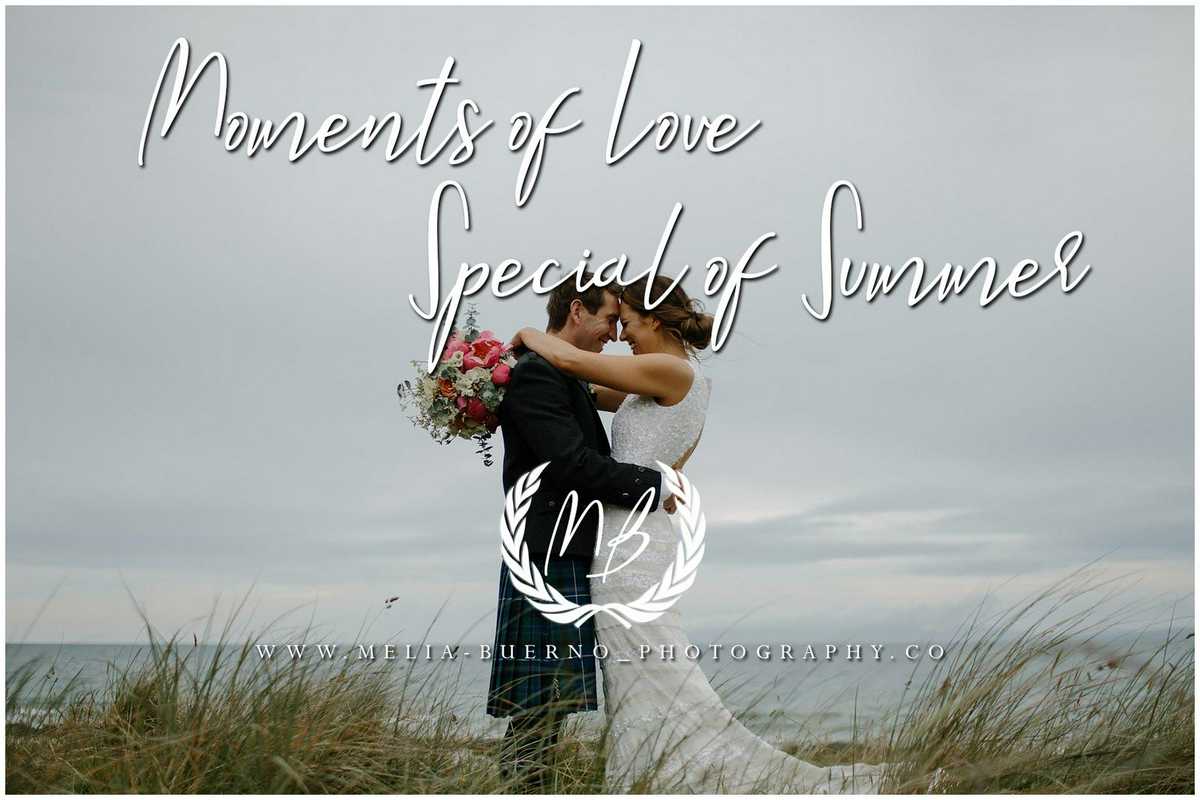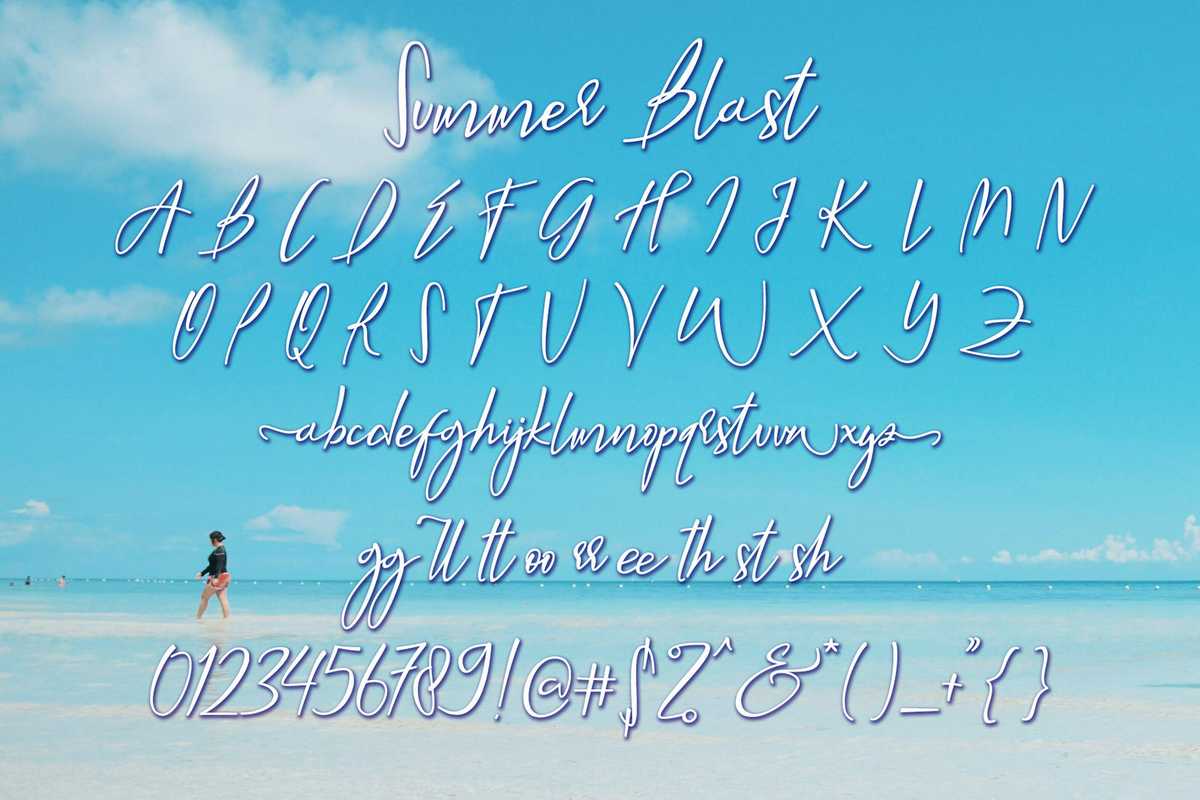
SummerBlasts是一款风格独特、精致的书写字体。它的设计风格多样,需要个性化的风格,如婚礼庆典、感谢卡、婚礼、问候卡、徽标等等。此字体经过编码,意味着您可以访问这些符号和Swashease!SummerBlasts是一款风格独特、精致的书写字体。它的设计风格多样,需要个性化的风格,如婚礼庆典、感谢卡、婚礼、问候卡、徽标等等。此字体经过编码,意味着您可以访问这些符号和Swashease!